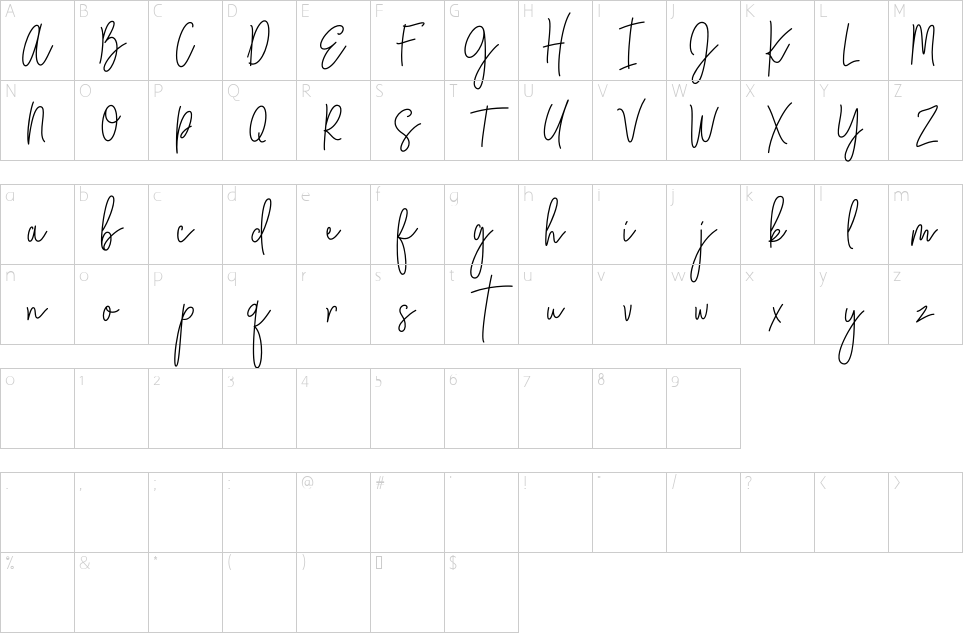
City Streetwear Font
Aqui está uma descrição para a página de download da fonte ‘City Streetwear Font’ que segue as instruções fornecidas: A City Streetwear é uma elegante e sofisticada fonte gráfica, perfeita para aqueles que procuram um estilo único e atemporal. Desenhada por Cindy Kinash, esta font oferece o ideal em variedade de estilos – desde linhas leves até texturas mais vibrantes, tudo com um toque de streetwear. Seja para aplicativos digitais ou impressão em material de merchandising, City Streetwear trará seu projeto a uma nova dimensão de originalidade e estilo. Com 5844 downloads, você pode estar certo que os designers procurando algo diferente encontraram o ideal. Esta fonte é um excelente escolha para aqueles buscando incorporar personalidade e atitude nas suas criações digitais ou físicas. Seja você designer gráfico, impressão de camisetas, criador de logomarcas – City Streetwear está pronto para ajudá-lo a destacar sua marca. Compre agora e inicie seu projeto com uma paleta de opções que não apenas dura horas em criar um design único, mas também reflete o poder da street culture no mercado atual.
Mapa de caracteres da fonte City Streetwear Font